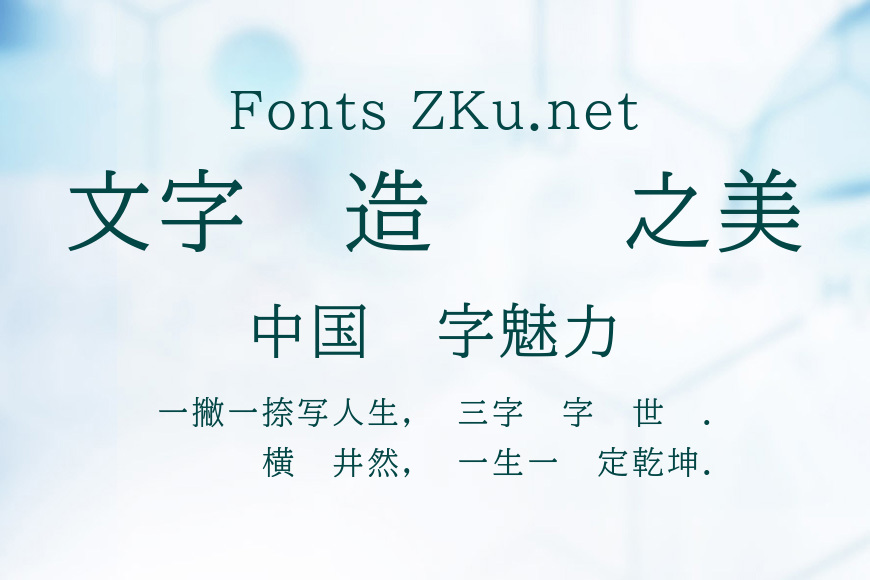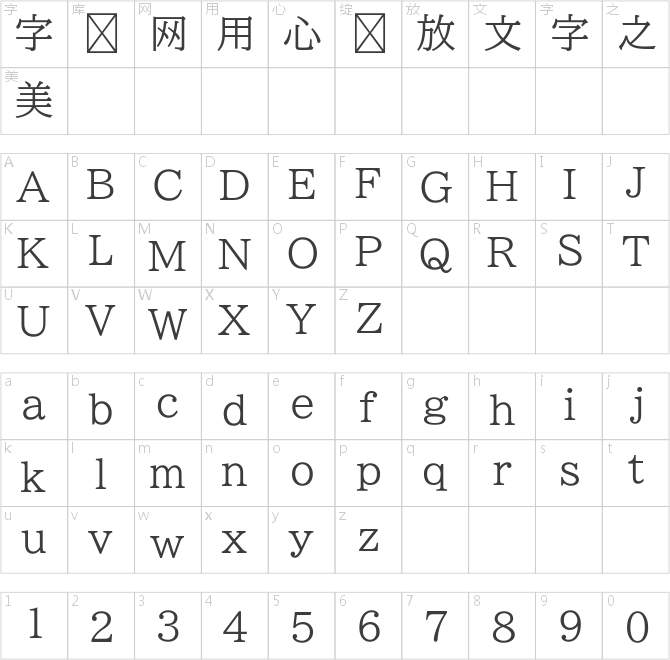
森泽UDP明朝 详情页
字体名称: 森泽UDP明朝
字体类型: 日文字体
作者版权: 森泽
森泽UDP明朝
森泽UDP明朝介绍
森泽UDP明朝字体字库是一款让人赏心悦目、百看不厌的日文字体,适合各类广告和产品包装设计应用,字体大小5.87MB,格式为ttf字体,上传用户是快霸中国,作者/版权方为森泽